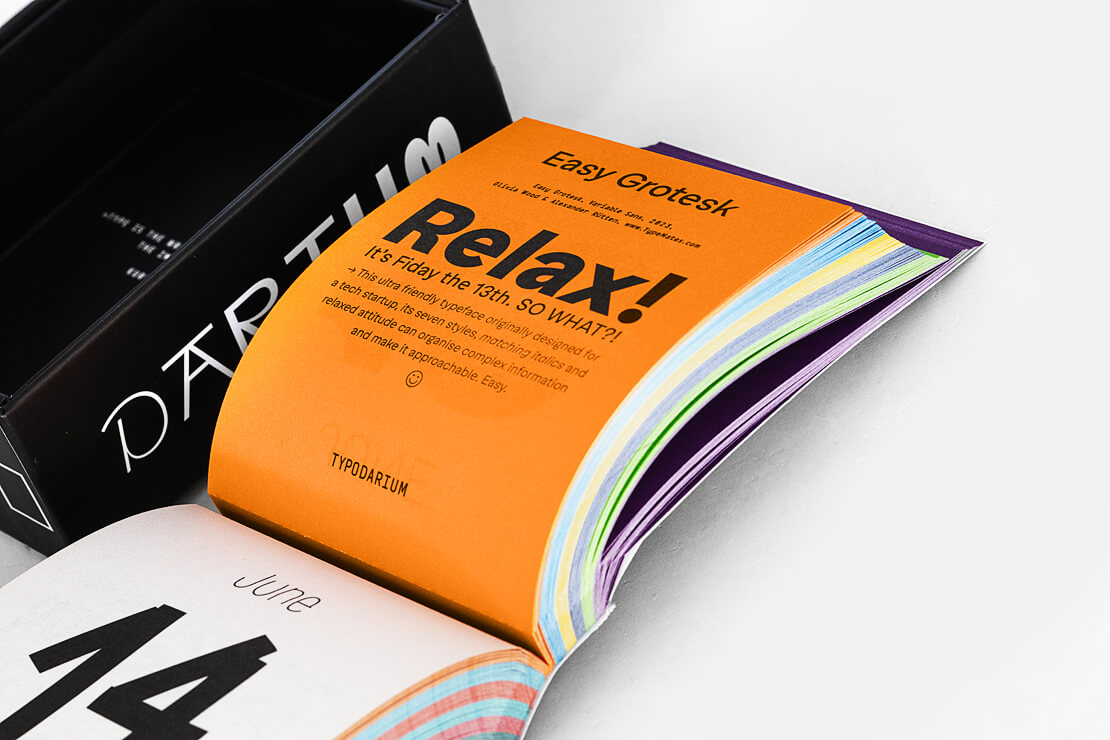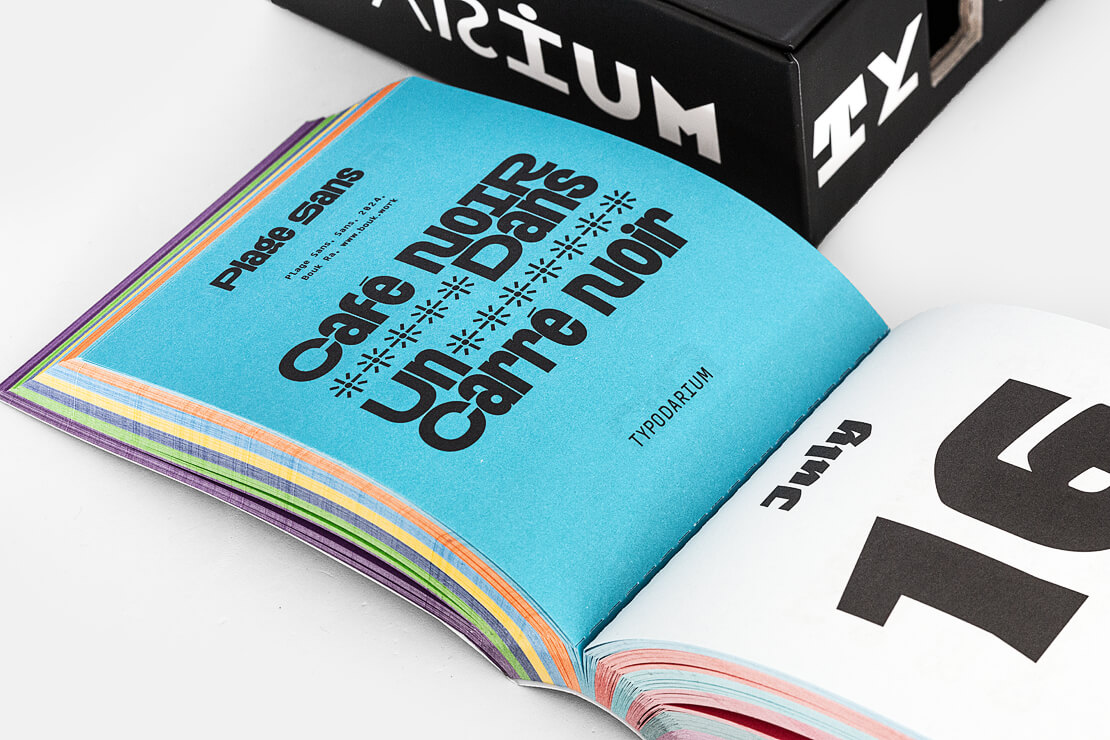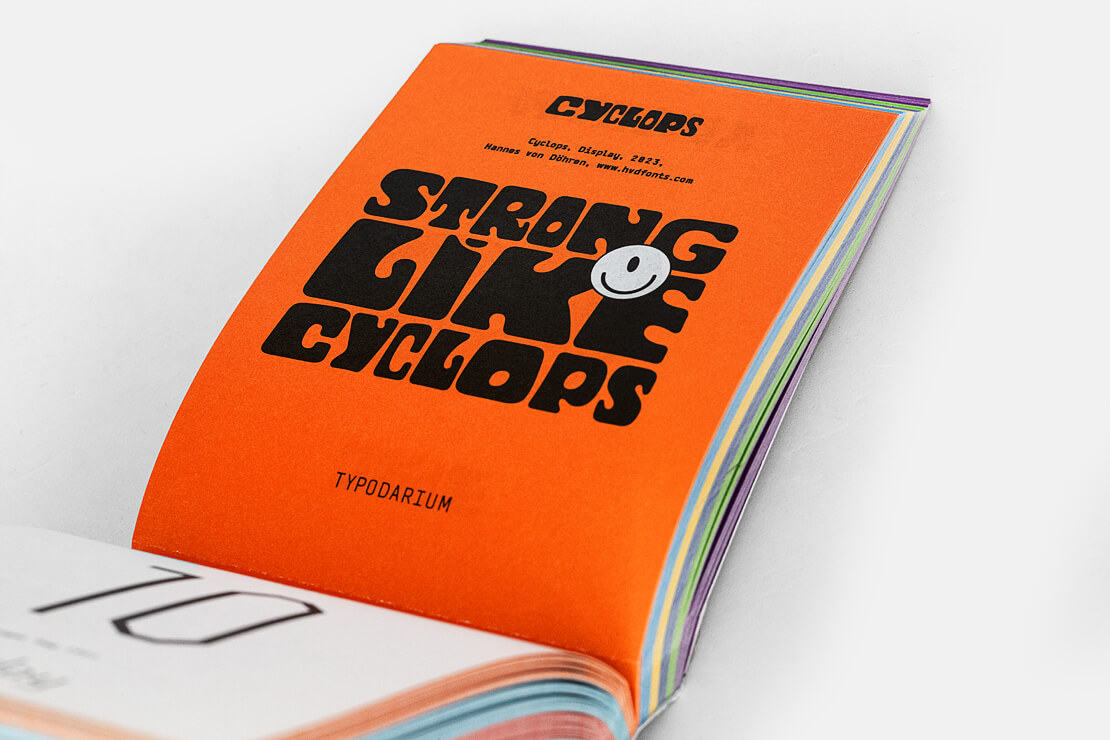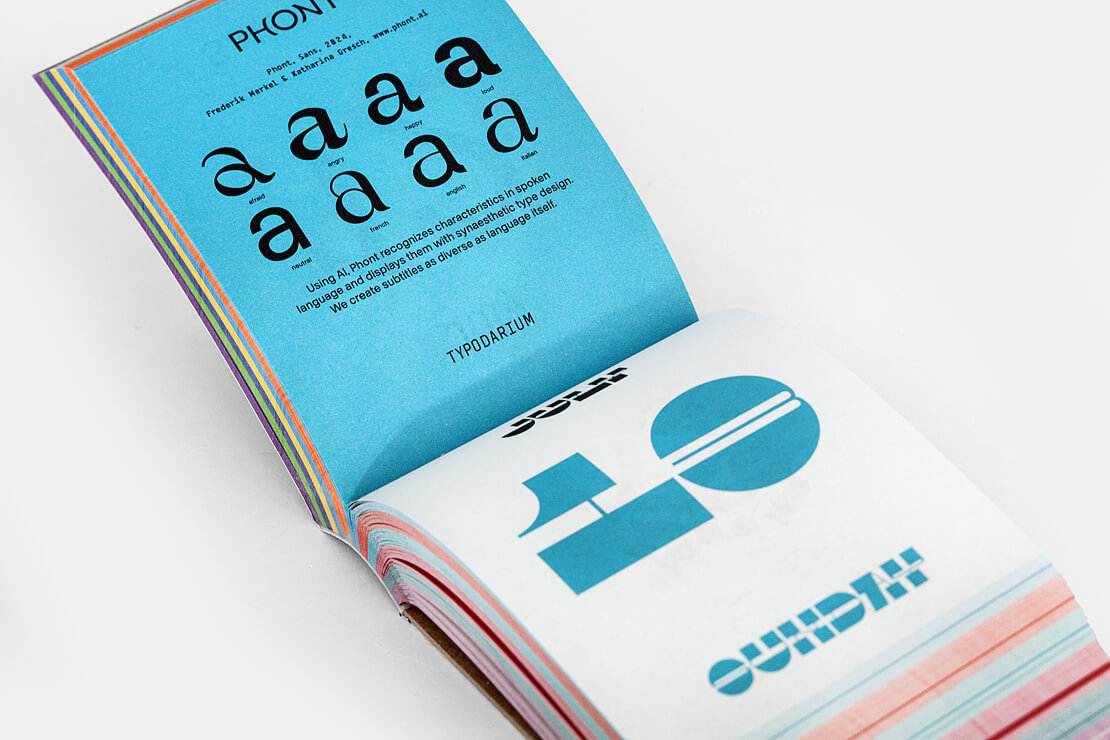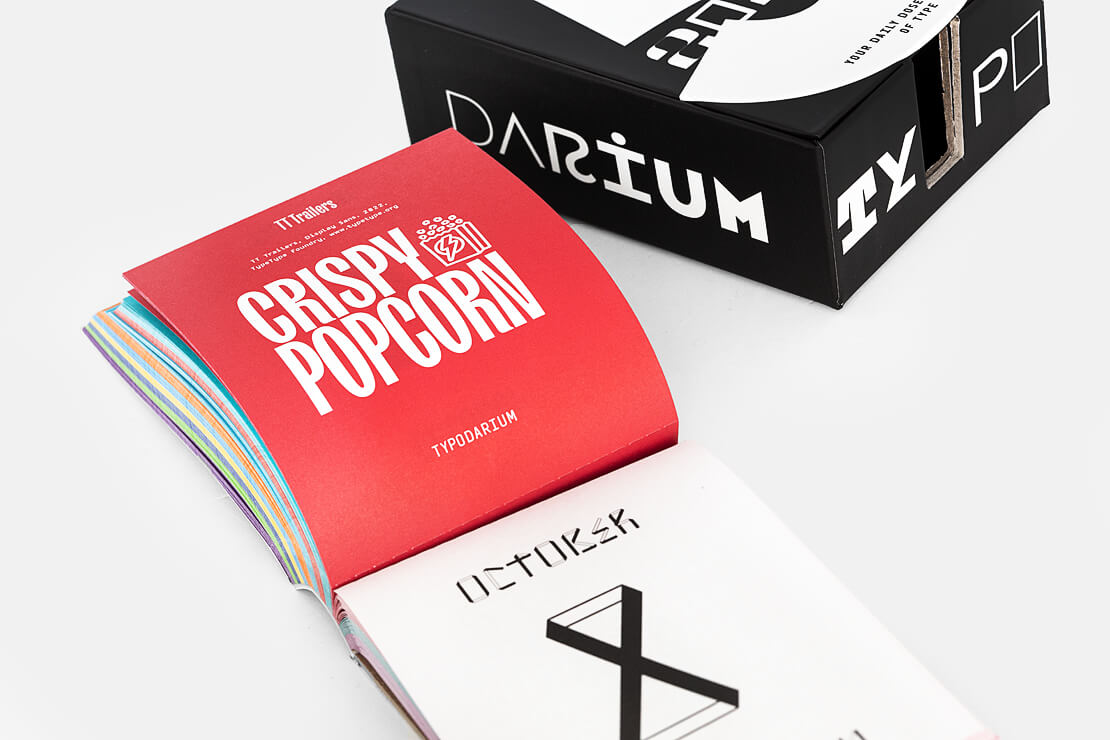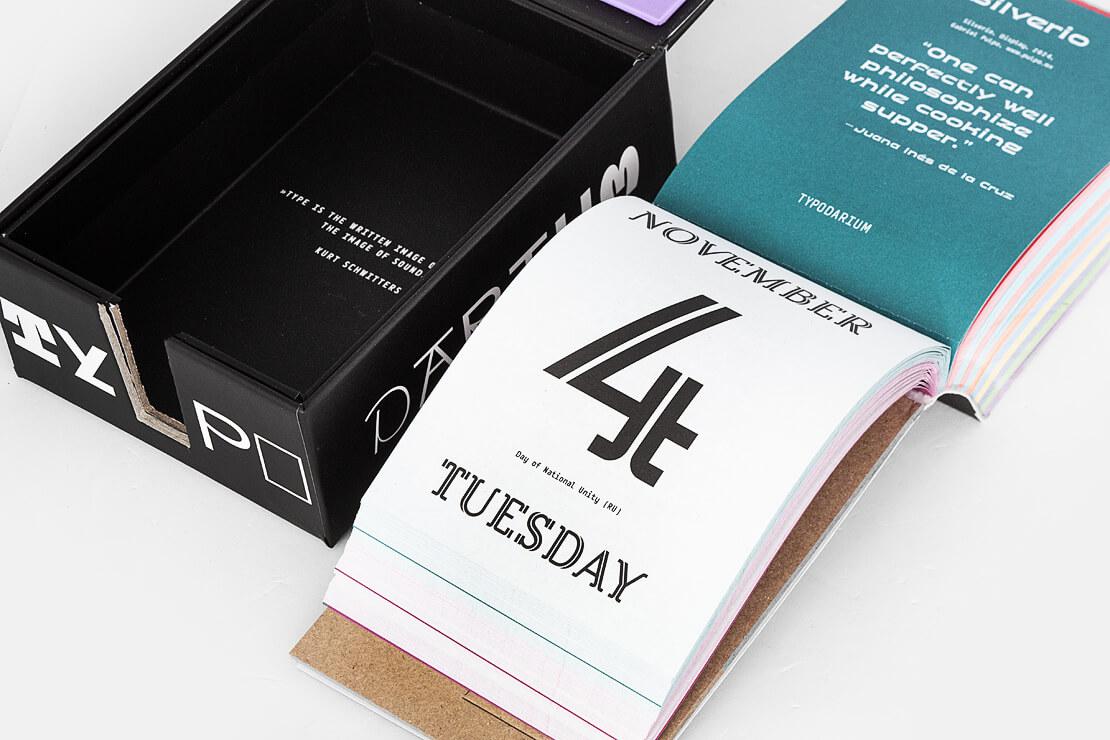
Typodarium 2025 erschienen
Das »Typodarium 2025« ist erschienen und bringt erneut frische Schriften und Typografie-Trends direkt auf den Schreibtisch. Die Herausgeber Raban Ruddigkeit und Lars Harmsen stellen in diesem Abreißkalender 365 Schriftarten für das Jahr 2025 vor.
Abreißkalender mit abwechslungsreichen Schriften
Das »Typodarium 2025« setzt seine Tradition fort, als Trendbarometer und Inspirationsquelle für die internationale Typografie-Szene zu dienen. Die Auswahl reicht von mutigen Displayschriften bis hin zu subtilen Fließtextschriften und bietet sowohl Neuentdeckungen als auch ikonische Klassiker. Jede Seite des Kalenders überrascht mit innovativen Schriftarten, die einen umfassenden Einblick in aktuelle Entwicklungen im Typedesign bieten.
365 Schriften im »Typodarium 2025«
Im »Typodarium 2025« gibt es insgesamt 365 Schriftarten von 357 Typedesignern aus 41 Ländern zu entdecken. An jedem Tag des Jahres wird eine neue Schriftart vorgestellt. Auf der Rückseite jeder Kalenderseite finden sich zusätzliche Informationen zu den Schriftarten, den Designern und dem jeweiligen Entwicklungsjahr. So wird das »Typodarium 2025« nicht nur zum täglichen Begleiter, sondern auch zu einem hilfreichen Nachschlagewerk für Schriftliebhaber.
Besonders an den Sonntagen steht der Kontrast in der Schriftgestaltung im Mittelpunkt. Fettschriften und filigrane Schriften, Aufstriche und Abstriche sowie serifenlose Schriften mit hohem Kontrast prägen die »Sonntagsbraten«. Diese Schriften bieten einen sehenswerten Wechsel im typografischen Alltag und bringen zusätzlich Dynamik in das Design.
Format und Verpackung
Das Format des Kalenders bleibt mit 8,5 x 12 cm unverändert. Jede Ausgabe kommt in einer stabilen Sammelbox, die sich zur Aufbewahrung der abgerissenen Kalenderseiten eignet. So kann das »Typodarium 2025« auch nach Ablauf des Jahres als persönliches Archiv und Inspirationsquelle dienen.